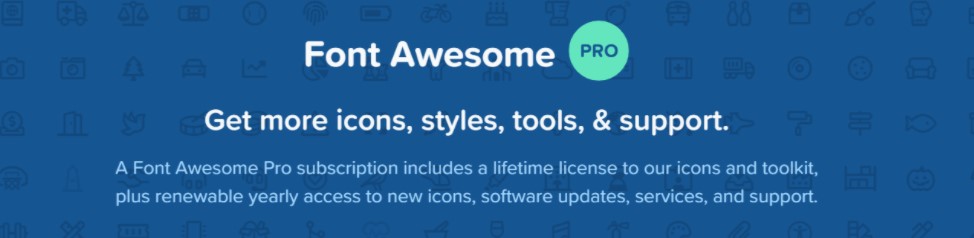
Fontawesome Font Awesome Pro v5.7.0
[Fontawesome] Font Awesome Pro v5.7.0
Font Awesome Pro - новая версия иконочного шрифта и CSS-инструментария.
Font Awesome PRO предлагает вам масштабируемые векторные иконки, которые вы можете с легкостью персонализировать - размер, цвет, тени и все, что можно сделать силами CSS. В новой 5.4.1 версии были добавлены 379 иконок.